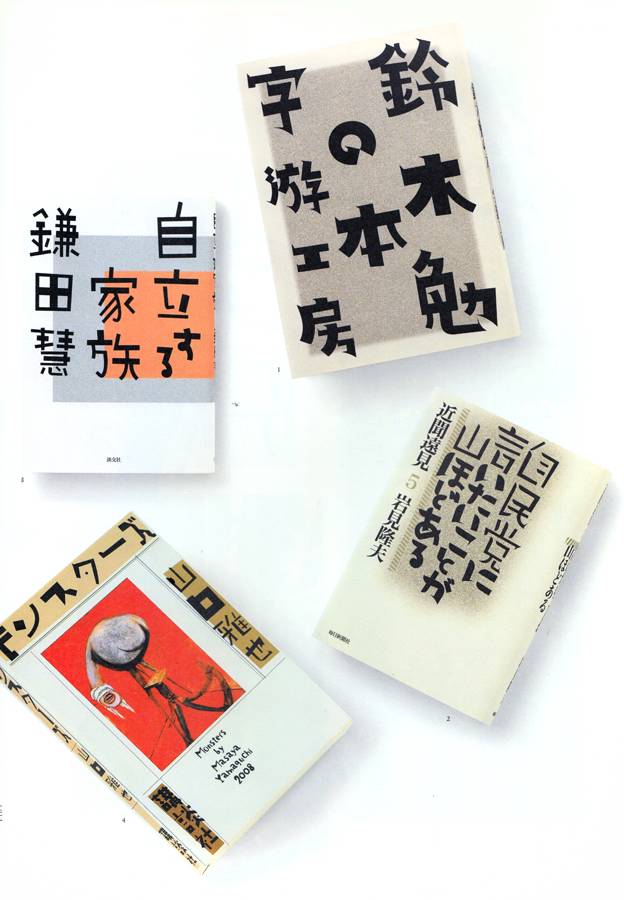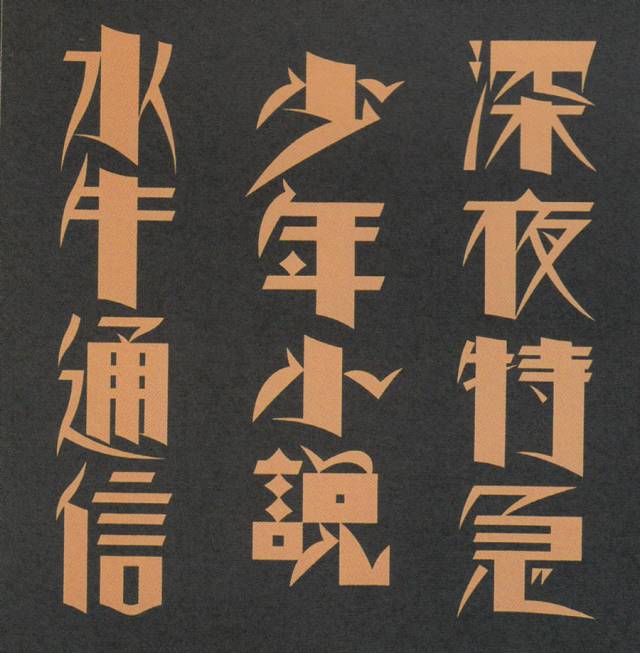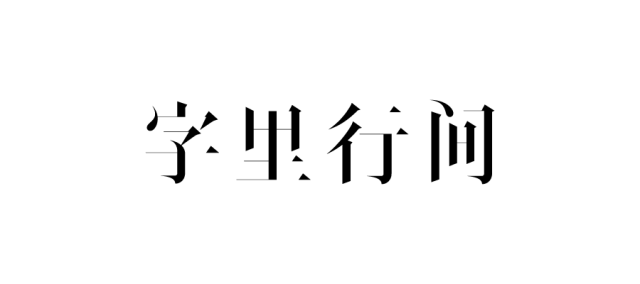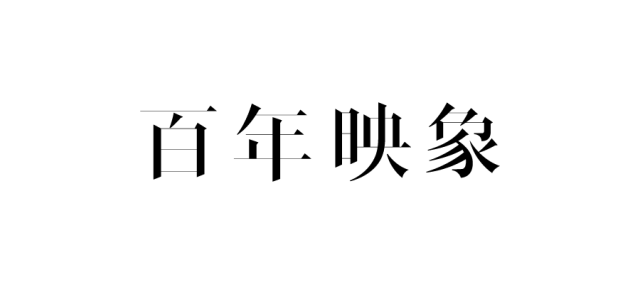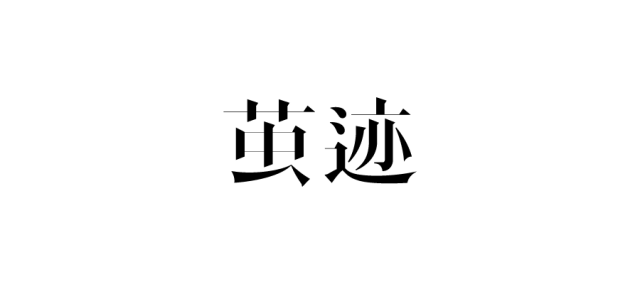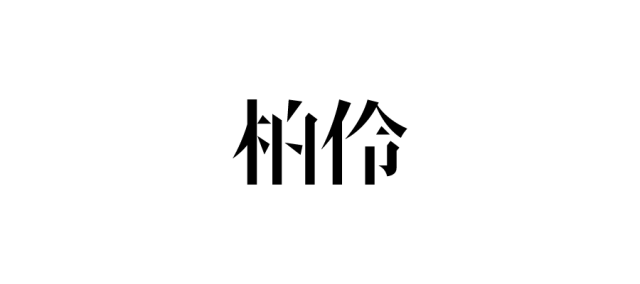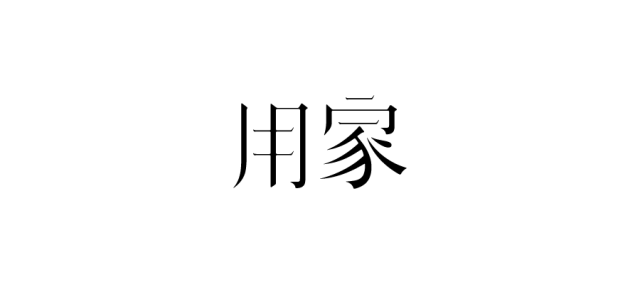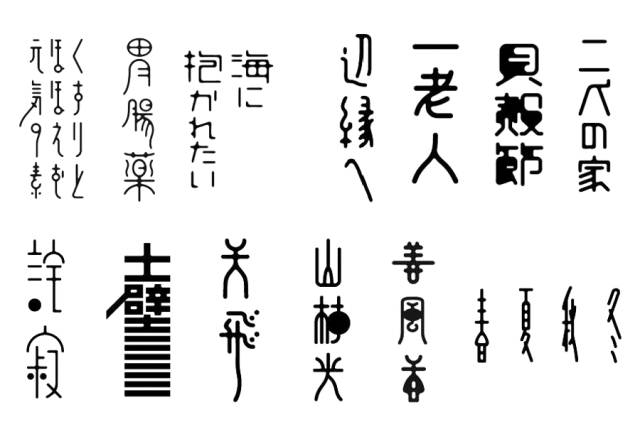
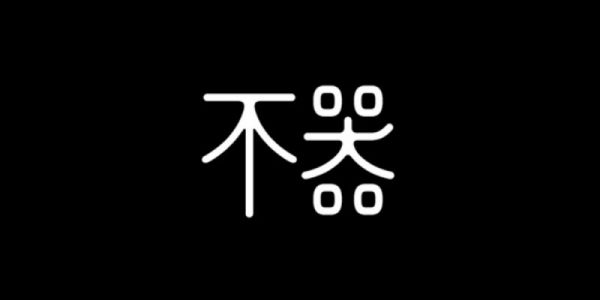
大师们的专用字型风格
{{tag.name}}平 野 甲 贺
2011年3月号的《idea》是平野甲贺的特辑,真正在中国熟知是王志弘装帧出版的《我的手绘字 平野甲贺》。最近平野甲贺为鸟海修装帧的书籍《文字を作る仕事》,同样是类似的字型,可说是“一招儿鲜,吃遍天”。
试想如果在大陆,客户应该会介意这种相似性。或者设计师本身也会抵触这个方式,靠一种风格营生,似乎会给人不思进取、江郎才尽的感觉。但在日本貌似还颇受欢迎。
题外话,我在翻看他最早的作品时,发现了下面的字型,设计于1980年。
与民国美术字时代的风格颇似,也许,只是也许平野甲贺是从那个时代的字型中汲取灵感,再融合自己和当下的审美趣味,慢慢变成了自己的设计语言。下图是我收藏的一本民国书《非尘美术图案文字全集》中的字型,可以感受下。
平野甲贺的字,仿制的难度在于随机的荒诞与有意的正常之间的平衡。
高 桥 善 丸
他的名字就是他的字型风格,善长圆(丸)体,喜欢用圆形(丸),而且很高。视觉形式很篆书。圆头行笔,瘦长,经常有很舒展、延长的笔画,笔画交叉处的磨损效果。最近也出版了自己的作品集《ここちいい文字 -ロゴタイプや書体のデザイン手法》。
下图是李阳冰的篆书,可对比来看之间的微妙关系。
2012年我设计的一款字型“墨茶”,现在看应该是受他的影响。
这个字型和组合形式也被很多人借鉴过。比如下面两个,这样的借鉴并没有问题,只是可以做得更好一些,比如“孝文家茶”的英文字体太拙计了。中文都只看到了形,并没有触及到篆书这个内核。
2016年又有一个类似风格的字型,现在看比2012年的“墨茶”更内在一些。同样有一个“器”字,笔画交叉处的圆角类似,但整个结构和气质却不同。所以借鉴可学形,神必须是自己的。
高桥的字,仿造的难度在于对篆书理解。
浅 叶 克 己
浅叶克己,研究东巴文字。喜欢研究书法,写毛笔字。他也有自己的专用字型,简单形容就是几何形的单一、锐利、坚实与毛笔的多变、柔软、虚幻的结合。
大概也是五六年前设计的一款字样,应该是受他影响。因年代久远不记得当时的情景,这个字样的源文件都找不到了,图片是从很早前的博客找到的。
浅叶的字,仿造的难度在于几何和水墨的对立和融合。
私 家 宋
回顾自己这些年来的作品,“私家宋”似乎逐渐变成自己的风格。这是一款横如发丝、竖笔适中、结构参考古体楷隶书写、锐利、线条极度干净的宋体。很多委托人都被她征服。
风格有什么好处呢?目的明确、效率提高。比如私家宋,喜欢这样风格的委托人会找到设计师,又因委托人有明确的设计诉求,而设计师也在这个风格中游刃有余,会很大的降低沟通和设计的时间成本。又因为其他设计师仿造风格的难度形成的独特性,不会带来设计费的降低。唯一的弊端可能就是重复作业带来的枯燥。但像平野甲贺、浅叶克己那样的字型,每一次设计都会有很大的随机性,乐趣应该大于乏味。
私家宋,仿造难度在于对书法结构的融入和对曲线的极致控制。比如之前看到有同学借鉴“字里行间”的字型。下图左为私家宋,右为借鉴款,对曲线的控制和审美力直接影响了字型的视觉感受。
说了这么多,我领悟到,一个追求自我实现的设计师,必须要有自己不可仿制的风格。不管这个风格是无意识形成,还是刻意追求的。这个风格必须除了视觉形式的独特,还必须有超越形式的审美控制力。
以前的灌输的观点更多的是,设计师要尝试各种风格,不能被定型,会被黑只会这一种设计语言。现在,信息交流共享变得如此简单的时代,没有标签没有风格,不会被人注意。
风格在某种角度,是在同一个方向上的达到异于常人的深度。可以是这个方向让人新鲜,形成风格;也可以是方向很平常,因足够纵深而发掘出新鲜,形成风格。